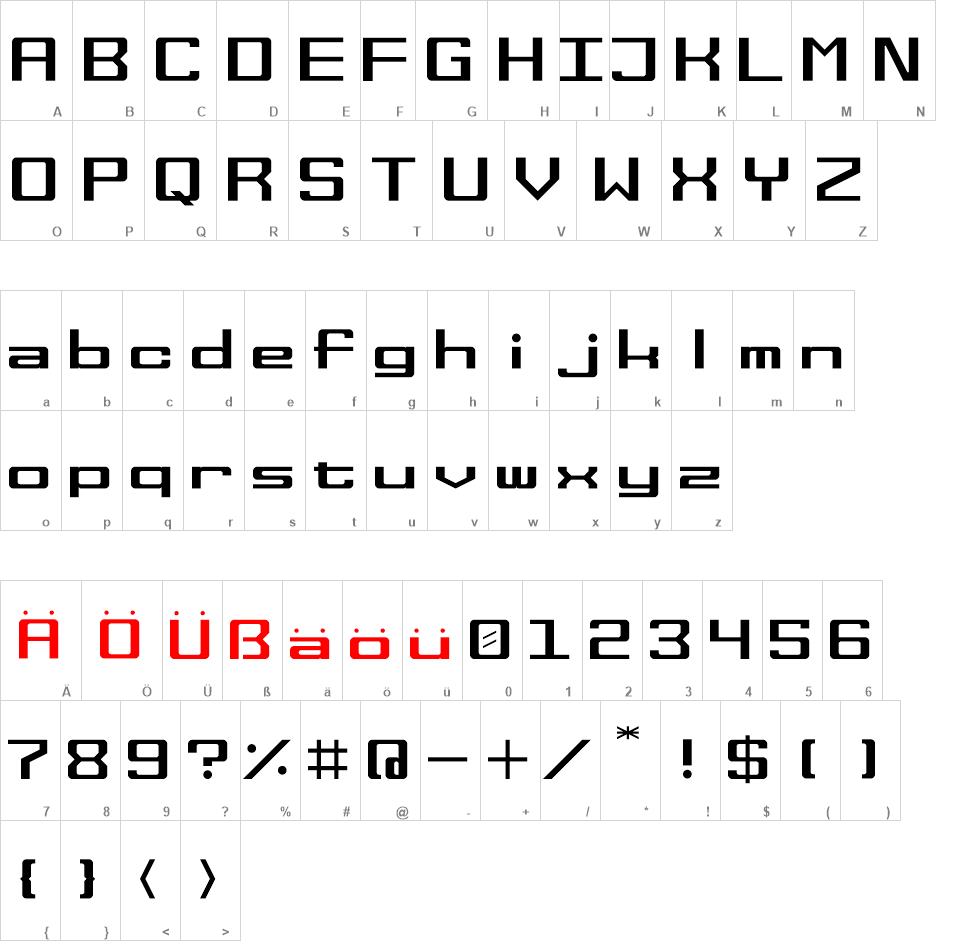
Space Wham
Space Wham font
Space Wham
Ein leicht chimäres Science-Fiction-Design ohne Bezug zu Space Blam, Space Cram, Weltraumdamm, Space Fam, Space Flam, Space Gram, Space Ham, Space Jam, Space Kazaam, Space Ma'am, Space Pram, Space Ram, Raum Sam, Space Slam, Space Tram oder Space Yam.
Um dies zu erreichen, versuchte ich eine Harmonie zwischen Winkeln und Kurven zu erreichen. Sie können es besonders gut auf "B" und "&" sehen.